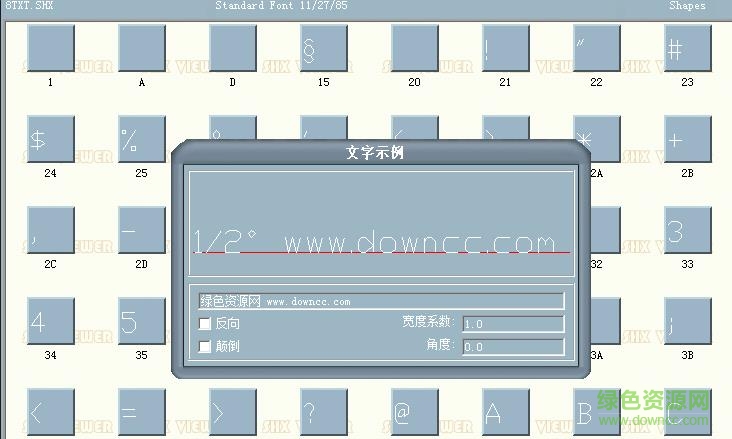
txt8.shx字體能夠打出眾多的符號(hào)讓你在使用的過程中輕松制作所需的圖形符號(hào)進(jìn)行運(yùn)用,讓人能夠一目了然圖紙內(nèi)容,帶給工程師們最佳的cad制圖體驗(yàn)!
cad字體擁有大字體與形文件的區(qū)別,能夠帶給用戶們不同的使用效果,字體文件將讓你隨心的輸入各類字體,而不出現(xiàn)系統(tǒng)問題。